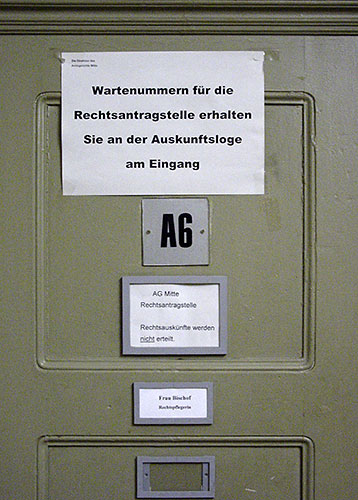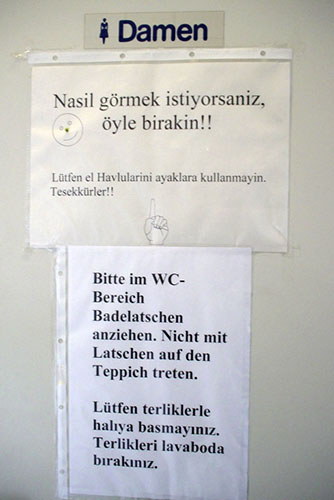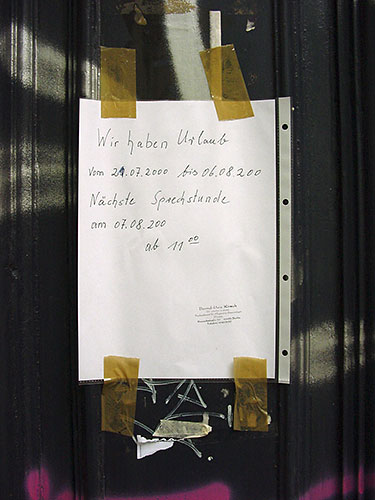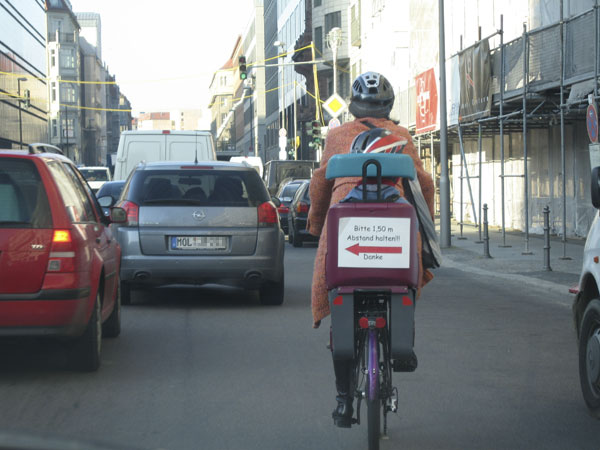
Fontnaepfchen 6: ZettelwirtschaftEin Laserdrucker im Büro verwandelt jedes Sekretariat in ein
Schilderwerksztatt. Und so erfreuen wir uns in Behörden und
öffentlichen Einrichtungen an selbst gestrickten Hinweisen, die manchmal
sprachlich, manchmal gestalterisch daneben gehen. Wenn beides zusammentrifft
![]() ![]() Hinweise in der Damentoilette der Sehitlik-Moschee in Berlin Neukölln ![]() Hierarchisch gegliederte Anweisungen, wie hier im Amtsgericht Berlin Mitte, gehören zur hohen Kunst der deutscher Behördenbeschilderung ![]() Schmierfing-Publishing: Wer keine vernünftige Urlaubsanzeige anfertigen kann, kann auch nicht richtig bohren ... Zahnarztpraxis in Berlin, Prenzlauer Berg ![]() Fast schon wieder gut: Hinweis für dicht auffahrende Autofahrer am Fahrradkindersitz; Art Direction & Driving: Imme Leonardi Photography: Alessio Leonardi Vielen Dank. Herausgegeben: Di - November 1, 2005 at 01:15 nachm. | |